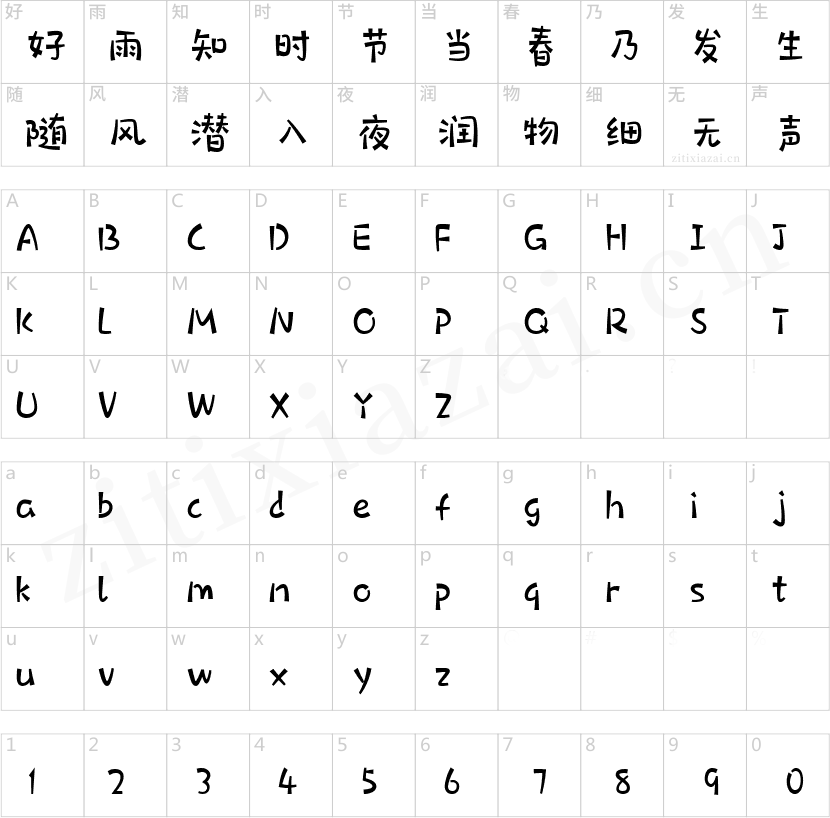
字魂157号-萌趣兔兔
字魂157号-萌趣兔兔,这款字体结构工整、笔画清晰,兼顾美观与易读性,适用于标题、正文、海报、包装、LOGO 等多种场景。字形优雅稳定,风格百搭耐看,适配日常排版与创意设计,让文字呈现更舒适、更具质感。字魂157号-萌趣兔兔一笔一画,皆是细节,以均衡的比例、流畅的线条打造舒适视觉体验,字形端正大气,风格简约现代。无论是商业设计、品牌宣传还是日常排版,都能轻松驾驭,让文字更有格调与力量。字魂157号-萌趣兔兔字体下载。
字魂字体字小魂萌趣兔兔字体是由字魂创意字库设计并生产的一款可商用的字体,被收录于字小魂系列。该字体支持GB-2312标准,包含6763个中文、字母、符号和数字,字体类型偏向创意字体,具有活泼、动漫、可爱、时尚的风格,在市面上广泛用于印刷品&包装、海报企宣、餐饮食品等场景。